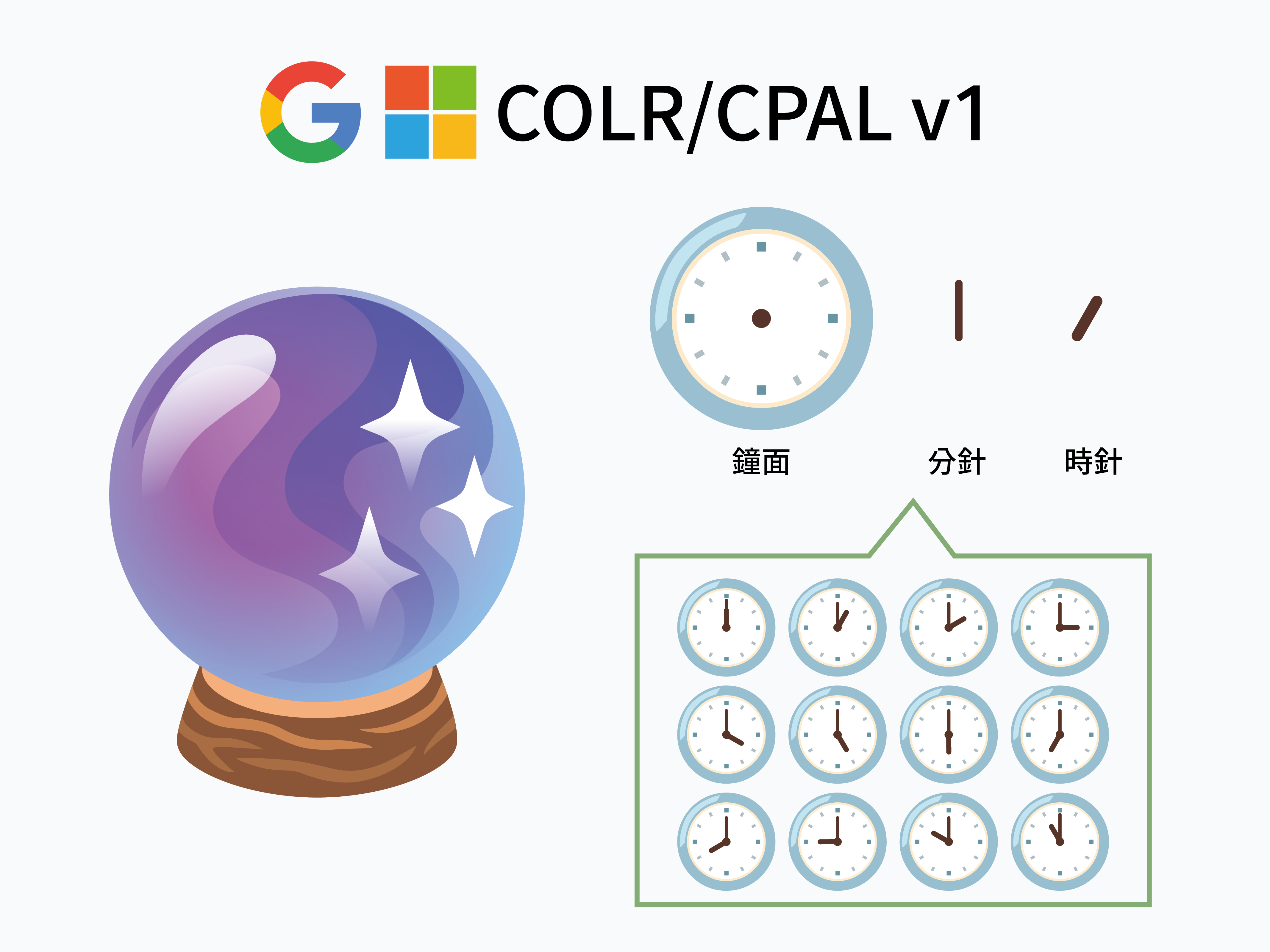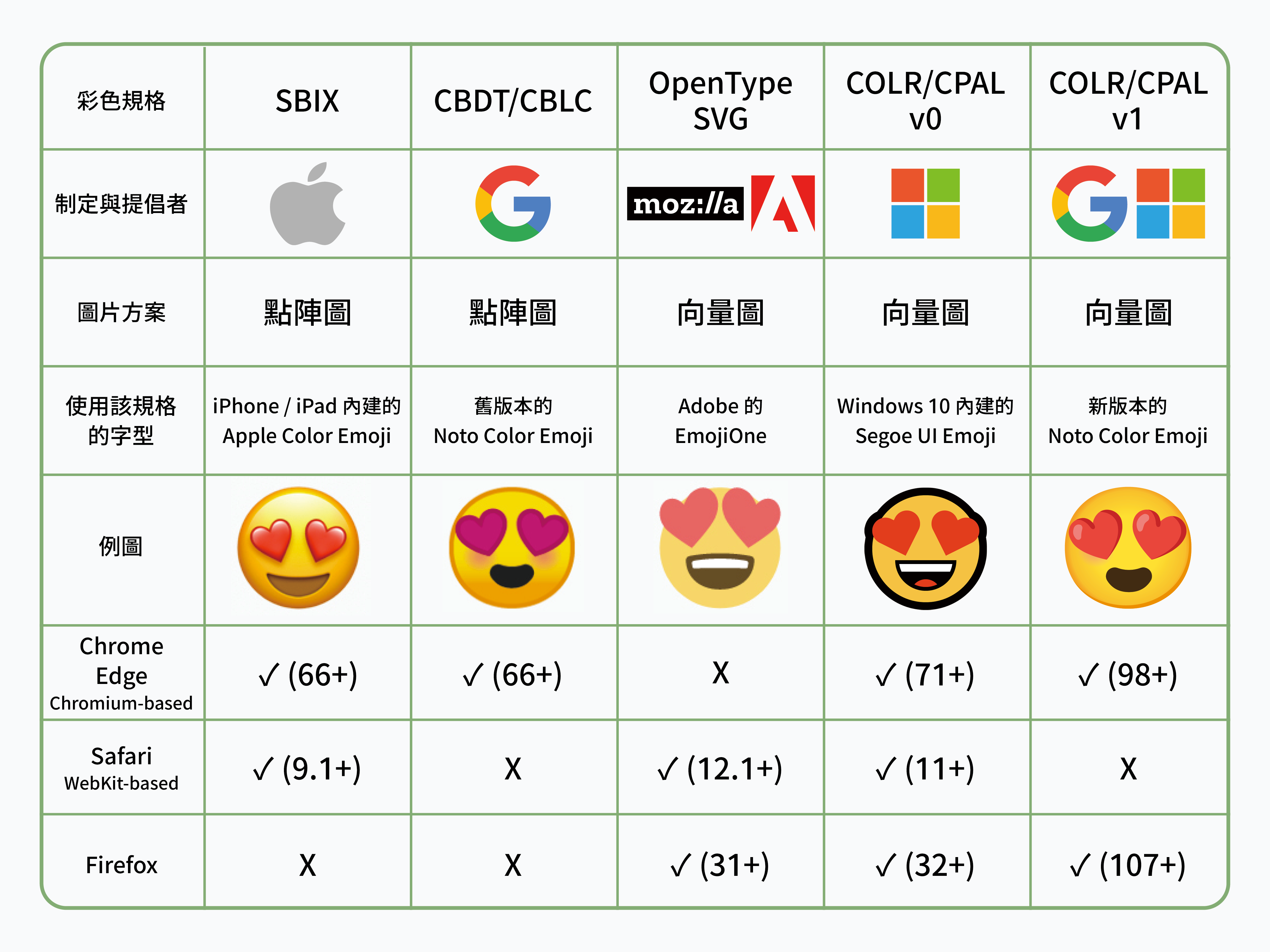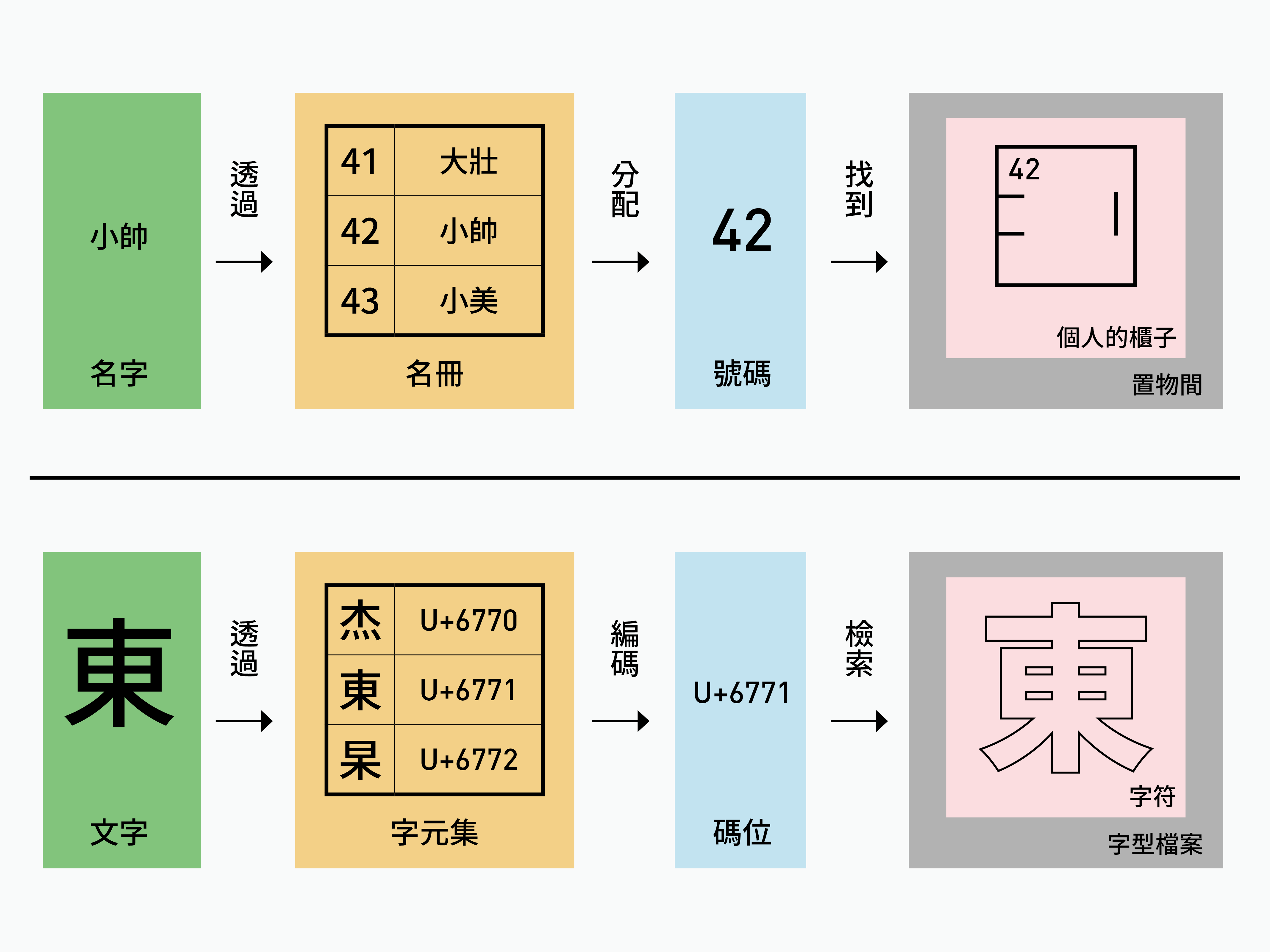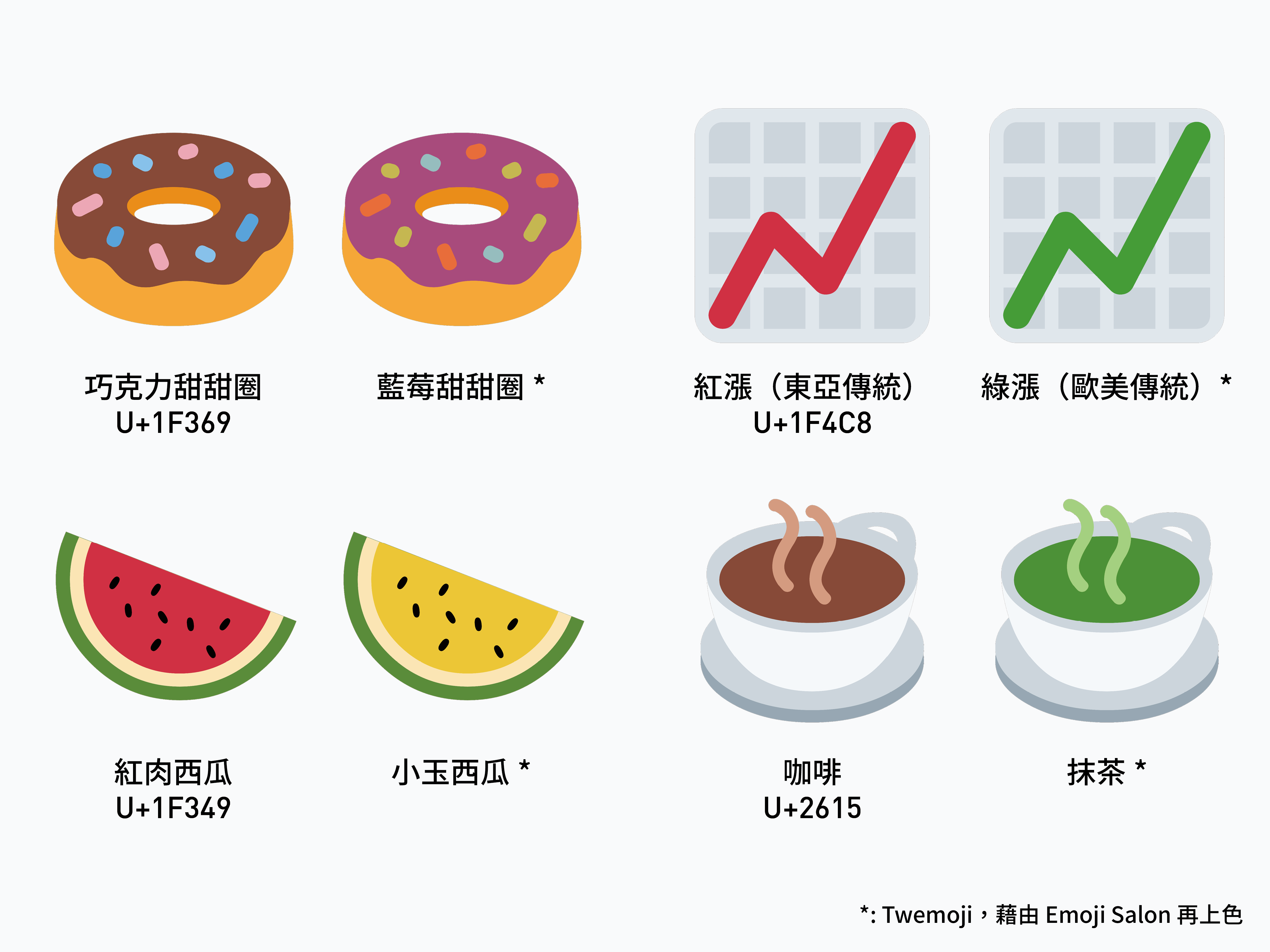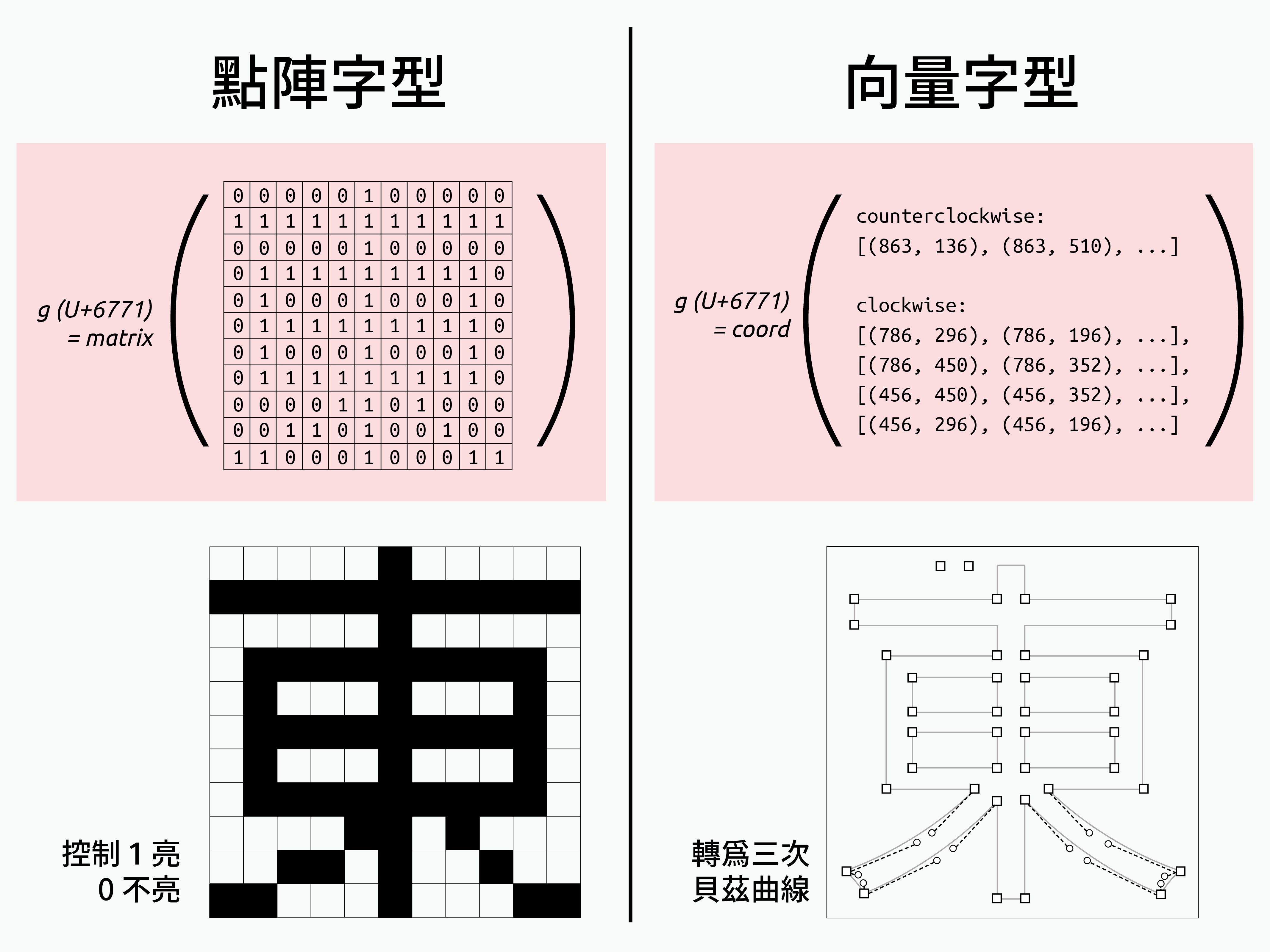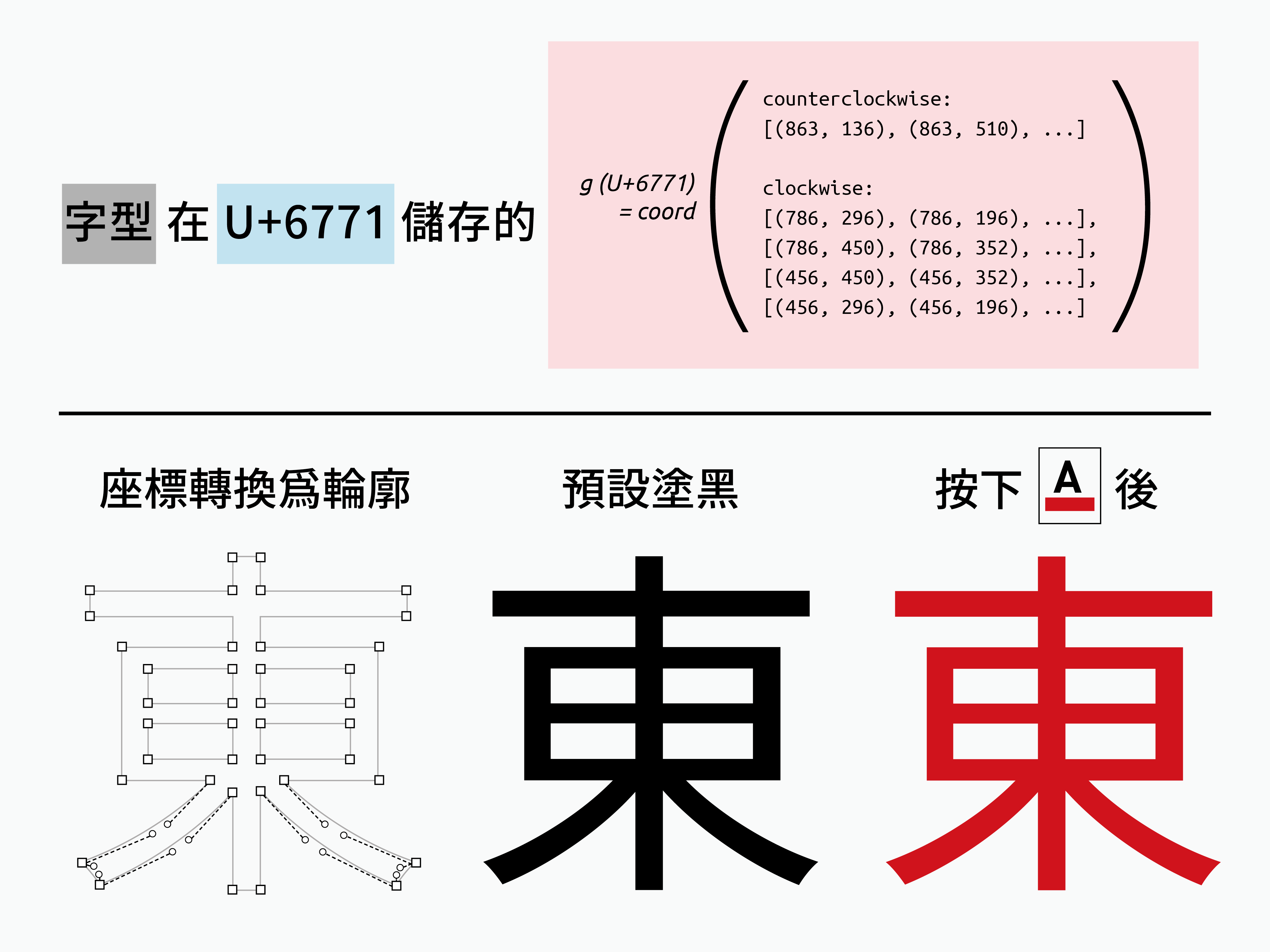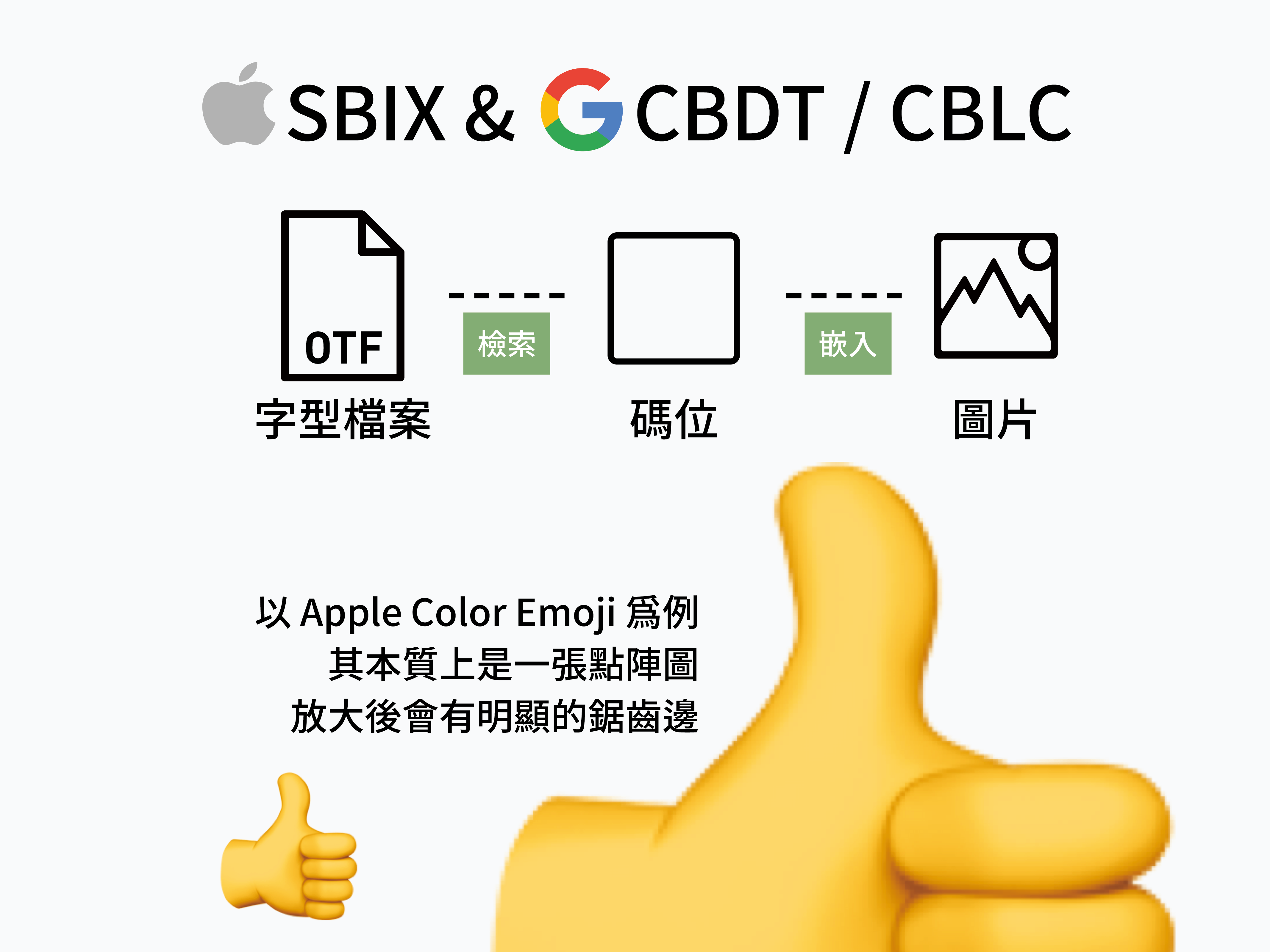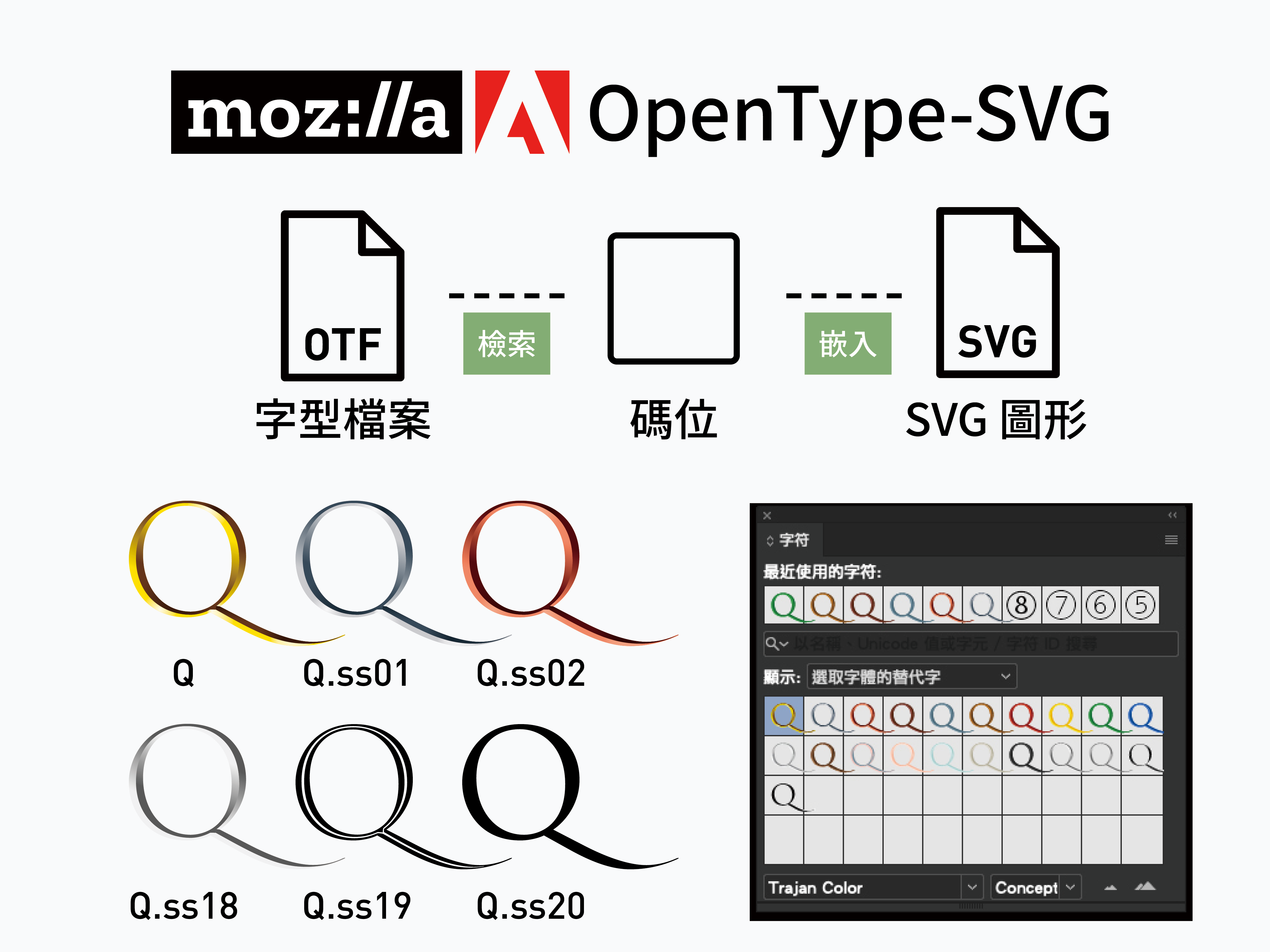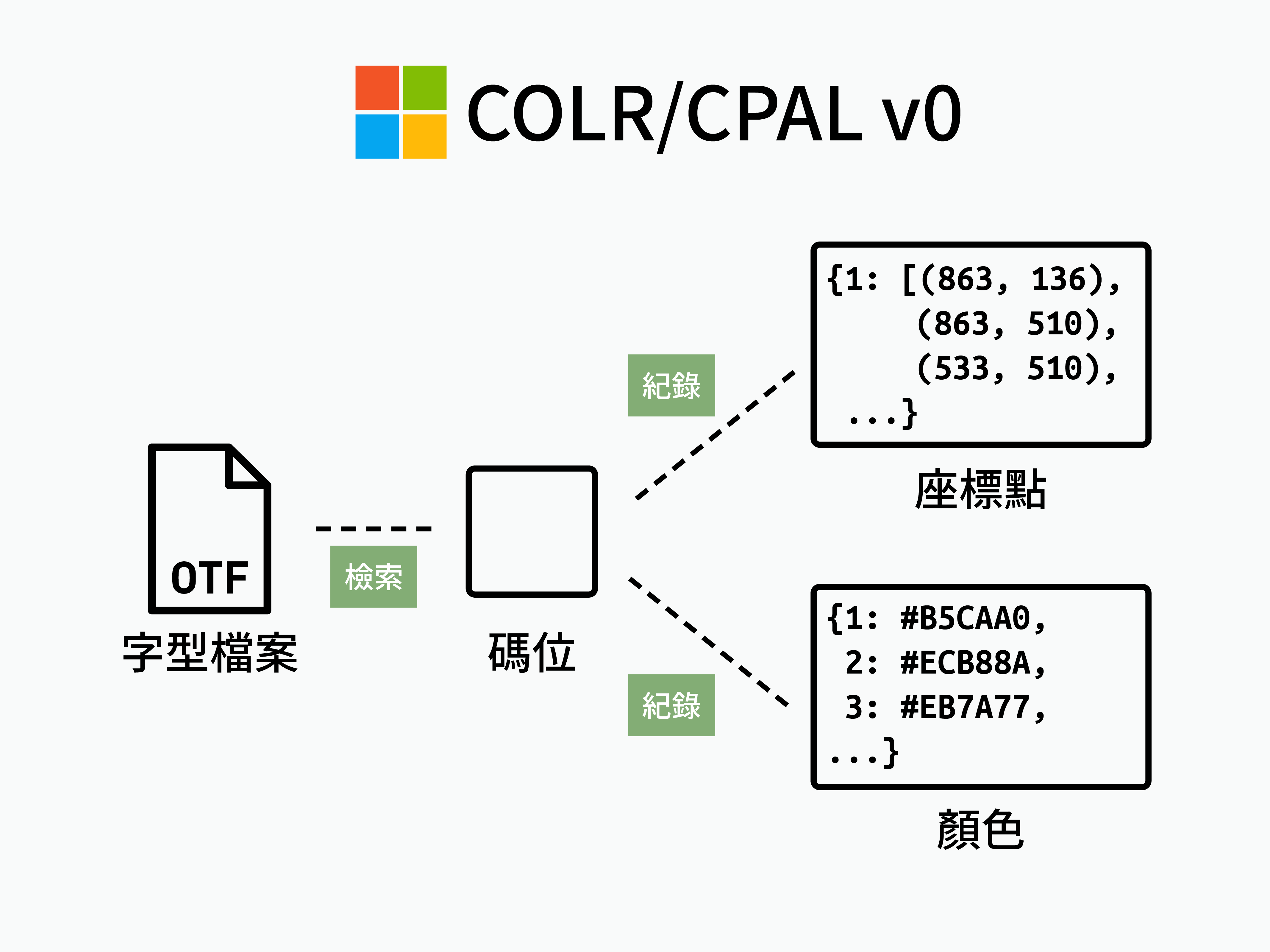
[Tech] 從黑白到彩色:彩色字型的秘密
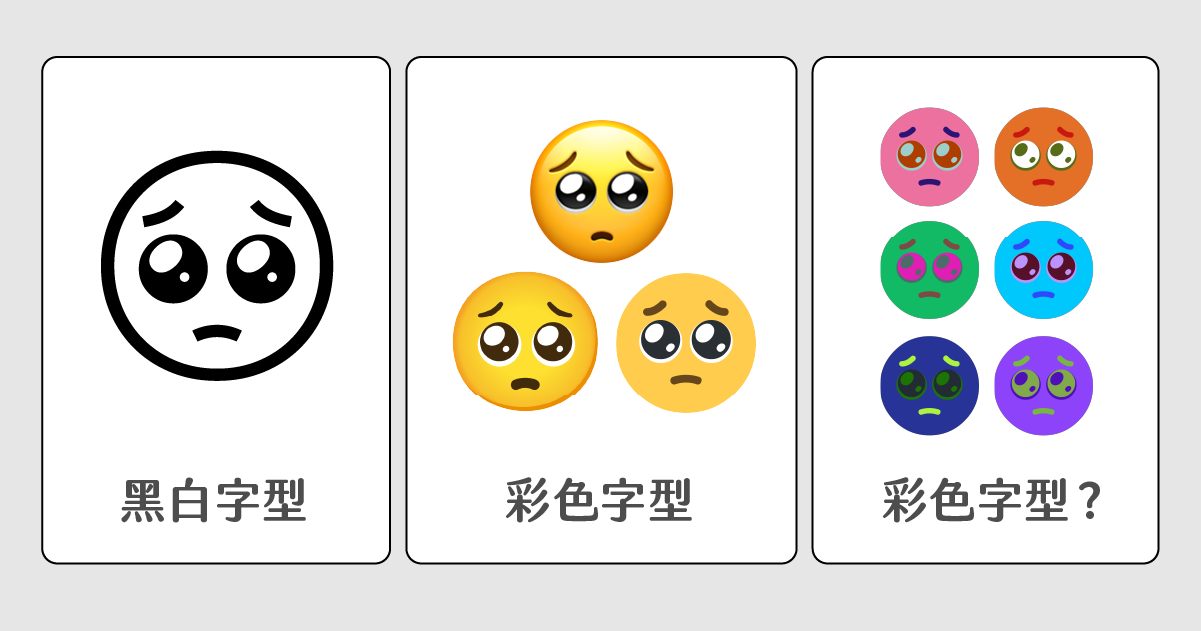
碼位與字符的關係
想像你今天要在健身房裡面租一個置物櫃,為了方便管理,櫃檯會把你的名字加到會員名冊上,並為你分配一個號碼,像是第 42 號;你則可以透過這個號碼,在置物間中找到屬於你的櫃子放衣服和毛巾。
電腦也是一樣,為了讓只理解二進位的機器認得人類的語言,我們必須透過字元集(character set),替每個文字(character)分配獨一無二的碼位(code point),讓電腦可以透過碼位,從字型檔案中檢索出對應的字符(glyph)。
我們可以很簡單地從置物間裡,透過編號找到櫃子的位置。但這個編號本身並不會記載我們在櫃子裡面放了什麼。所以在實際找到這個置物櫃之前,其他人沒有辦法藉由編號得知櫃子的內容。
同樣地,碼位只是提供了字符的指向資訊,告訴電腦在存取時,可以在 U+6771 的位置上找到「東」。但碼位本身並沒有揭露字符應該要長什麼樣子,必須等電腦找到字符之後,才能獲取「東」的輪廓外觀。
封閉曲線的顏色
至於這個「輪廓外觀」要怎麼儲存呢?在數位字型概念剛誕生的時候,大多都以矩陣(matrix)的形式紀錄,藉由 1 與 0 來控制顯示器的亮與不亮。而現在的字型檔,則大多以向量(vector)的形式儲存,透過多個座標點和參數曲線來構建字的外觀。
對於向量格式的字型而言,字符資訊儲存的都僅僅是座標而已,並沒有任何的技術規格要求曲線內部一定得是黑色的。我們之所以看到黑色的字,其實是軟體的自作主張,「預設」將封閉的區域都塗黑。
那麼字為什麼一定要是黑色的?從中世紀的手抄本到近代的印刷術,東西方不約而同都走上了白紙黑字的傳統。這或許是因為黑色更好的覆蓋在白色上,也或許是因為用來造紙的纖維大多為淺色、用來製墨的礦物大多為深色。總而言之,白紙黑字的習慣被這樣被繼承到了數位時代。
在預設之外,現在幾乎所有的文書軟體都支援換色的功能。不過,如同前面所說的,字型檔案本身僅僅紀錄了字符輪廓的座標,並沒有任何關於顏色的屬性,無論字被使用者換成紅色還是藍色,都只是對封閉路徑再著色而已。
帶來色彩革命的 Emoji
一直到 Emoji(繪文字)於 2010 年正式被收入 Unicode 6.0 標準後,這些五顏六色的酷酷東西才讓科技大廠們意識到,除了輪廓之外,「字」也應該要能有自己的顏色。
畢竟如果能顯示一隻彩色的卯咪,一定會比黑白的卯咪還要可愛 —— 當然,賓士貓還是很可愛的,但我們還是想要照顧一下橘貓族群!
可以說,Emoji 的標準化促使了字型規格的新革命——這次由四個陣營領銜,各自代表不同的作業系統與軟體,分別是 Microsoft (Windows)、Apple (iOS / macOS / Safari) 以及 Google (Android / Chrome),以及 Adobe - Mozilla (Firefox) 聯盟,一場環繞色彩的規格競爭就此開啟了序幕。
Apple 的 SBIX 與 Google 的 CBDT/CBLC
想要顯示彩色的字符,最直覺的想法就是在原本放路徑座標的櫃子裡,改成放一張圖片。如此一來,電腦還是能透過碼位,檢索字型檔案裡面的字符位置,只是這次找到的不是座標點,而是一張圖片。
像是 Apple 提出的 SBIX(Standard Bitmap Graphics)與 Google 的 CBDT/CBLC(Color Bitmap Data / Color Bitmap Location)技術,就是將圖片連結到相對應的碼位,以此讓字型顯示彩色的字。
不過,透過這種方法顯示的字本質仍舊是點陣圖(bitmap),在縮放時會有明顯的失真。或許當初 Apple 和 Google 都沒想到會有把 Emoji 放到很大很大的需求,但使用者總是會有各種出乎意料的想法。
如果你的手邊有 iPhone,可以嘗試在 Instagram 的限時動態裡輸入文字和 Emoji,然後再把它們放的很大,會發現文字即使再大也不會有鋸齒邊緣,但當 Emoji 放大到某種程度後,就會變得模糊不清。
此外,因為字型檔案實際上是一堆小圖片的集合,SBIX 和 CBDR/CBLC 彩色字型的檔案尺寸都會偏大,除非是原本就內建在作業系統裡面,否則並不利於 webfont 的使用。
Adobe 和 Mozilla 的 OpenType-SVG
既然可以連結碼位與點陣圖,那或許也可以讓碼位和向量格式的 SVG 有所關聯。
Adobe 與 Mozilla 在此想法上開發了 OpenType-SVG 規格,這次是將 SVG 嵌入到對應的碼位上。只要是 SVG 能夠做到的事情,像是漸層效果、甚至是動畫,現在都能透過 OpenType-SVG 規格重新包裝成一個字型檔,當成是字來使用。
不過,因為一個碼位僅能連結一個 SVG 檔案,所以如果想為同一個字符設計多個造型,就需要將不同的設計拆分成多個替換字符(alternate glyph)。而根據 OpenType 的規範,同一個碼位至多允許 20 個替換字符,因此圖中的 Q 至多只能有 21 種樣式(本體 + 20 個替換字符)。
比較可惜的是,即使像是 Firefox 和 Safari 都支援 OpenType-SVG 規格的字型,但目前最主流的 Chrome 已經明確表示不會支援。因此,OpenType-SVG 的彩色字型,例如 Trajan Color,主要還是用在像是 Photoshop 或是 Illustrator 等 Adobe 桌面軟體上。
Microsoft 的 COLR/CPAL
而 Microsoft 主導的 COLR/CPAL (Color / Color Palette) 技術則和上面所說的「塞圖」概念完全不同——既然字型檔已經儲存了封閉路徑,只要再另外紀錄各個路徑要顯示的顏色,就能在不額外嵌入圖片的情況下表現出色彩。
我們可以將設計好的字拆分成多個圖層,分別指定各個圖層要顯示的顏色,再按照圖層的順序疊放在一起。比起額外儲存一堆小圖片,現在檔案只要紀錄路徑和對應的色碼即可,能大幅減少檔案尺寸。
此外,COLR/CPAL 雖然和 OpenType-SVG 一樣同為向量字型,在縮放時都不會失真,但 OpenType-SVG 是將顏色寫死在 SVG 檔案裡,而 COLR/CPAL 則可以在字型裡創建多個色盤(palette),每個色盤又可以分別設定各個圖層的顏色,不必使用替換字符來拆分不同的設計。
如果原本字型設計師的配色不符合我們的需求,我們可以針對某個色盤裡的某個顏色進行部分的覆寫,甚至全部都改成自定義的色票,這相當於將色彩的多樣性還給使用者,彈性更大。
以 Rocher Color 這套字型為例,其內建了 11 個基本色盤。預設的顯示會使用的第 0 個色盤(橘棕配色),而使用者也可以透過 CSS 裡的 base-palette 屬性來指定某個色盤,例如用 base-palette: 1 指定第一個色盤(粉紅配色),或是 base-palette: 7 來指定第七個色盤(薄荷配色)。
若是基本色盤裡面沒有喜歡的樣子,也可以透過 override-colors 的方法強制覆寫某個圖層的顏色,例如 base-palette: 1; override-colors: 0 #8D742A, 2 #87B377;,便是以第一個色盤為基礎,將第一個圖層替換成 #8D742A、第二個圖層替換成 jf 綠的 #87B377(編號由第零個開始數)。
改版的 COLR/CPAL v1
近期,或許 Google 也深感向量字型才是未來,逐步棄用自己的 CBDT/CBLC,選擇和 Microsoft 聯手,基於原本的 COLR/CPAL 格式,擴充出 COLR/CPAL v1 規格(原本的則被稱作 v0)。
新版本不但可以讓原本只能以單色疊放的圖層擁有漸層效果,還可以重複調用路徑。以下面的水晶球為例,旁邊閃閃發光的星星其實在檔案裡面只儲存了一個,剩下的都是借來的。而過去必須分別儲存 12 個鐘面和指針的整點 Emoji,現在也只需要一個鐘面和指針即可,除了節省空間,也方便設計師管理素材。
支援程度
目前,SBIX、CBDT/CBLC、OpenType-SVG 與 COLR/CPAL 這四個解决方案都已經被納入 OpenType 的標準裡面。雖然向下兼容了既有的彩色字型,卻也使開發者需要額外考慮規格不一所帶來的混亂。因此,在打算使用彩色字型時,必須額外考慮軟體的支援程度。
從表格中來看,主流瀏覽器對 SBIX、CBDT/CBLC、OpenType-SVG 的支援較差。至於 COLR/CPAL 規格,目前主流瀏覽器都支援顯示 v0,但 Safari 與使用 Webkit 核心的瀏覽器(在 iPhone 和 iPad 上的所有瀏覽器)則不支援 v1 版本。如果好奇自己的瀏覽器是否支援顯示特定規格的彩色字型,可以透過 ChromaCheck 或是透過 Can I Use… 網站來查詢。
至於軟體方面,微軟的 Office 在 Windows 與 macOS 上對於彩色字型方面的支援不一;而 Adobe 系列的軟體,至少必須等到 CC 2017 之後才能顯示彩色字型(Photoshop CC 2017+ / Illustrator CC 2018+ / InDesign CC 2019+ ),更舊的版本或許能顯示,但會沒辦法正常的儲存檔案與匯出。
在權衡之下,除了無法使用漸層效果這點較為可惜之外,作為主流瀏覽器和軟體的最大公約數的 COLR/CPAL v0 格式,已經成為當前最通用的業界標準之一,也是目前彩色字型的最佳選擇。
Emoji Salon
COLR/CPAL 可以分層設色、逐層替換的特性,大大的擴展了彩色字型的可玩性,我們可以透過 CSS 語法選擇性的覆寫圖層,就好像著色本一樣,為字符或是 Emoji 換上不同的顏色。
Emoji Salon 就是按照這個概念建立的網站,使用者可以切換不同的 Emoji,並透過下方的色號盤替換想要的顏色。之所以被稱做 Salon,是因為換色的過程就好像是在美容院(Salon)裡,為自己換上不同顏色的髮型與妝容一樣。
舉例來説,西瓜 🍉 (U+1F349),在多數的字型裡都是設計成紅肉西瓜,我們也可以填入黃色,將其改造成小玉西瓜;熱飲 ☕️ (U+2615) 則多被設計成咖啡的顏色,難道除了裝熱咖啡之外,就不能是熱牛奶、熱烏龍茶、熱抹茶嗎?
除了有趣之外,換顏色這件事也可以讓 Emoji 更因地制宜。舉例來說,由於 Emoji 源自日本,所以表示趨勢用的顏色是紅漲綠跌(東亞傳統上以紅為陽,紅的喜氣),但對於習慣綠漲紅跌的歐美來說卻是完全相反,此時就可以把上漲的 📈 (U+1F4C8) 改成綠色的。
最後,對於判色能力正常的人來說或許從未察覺,但有些 Emoji 的顏色被設計得太過接近與和諧,在色弱族群的人眼裡其實是很難分辨的,如果能另外換色加深對比度,讓顏色與顏色之間的差異性更大,就能解決少數族群的需求。
在我們無限的創意之下,搭配無數種可能的色彩組合和想法,依舊能為 Emoji 帶來無限的可能。